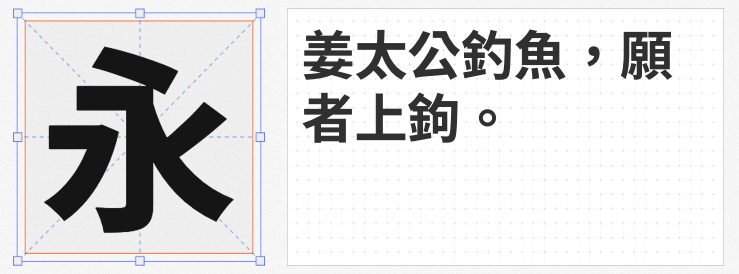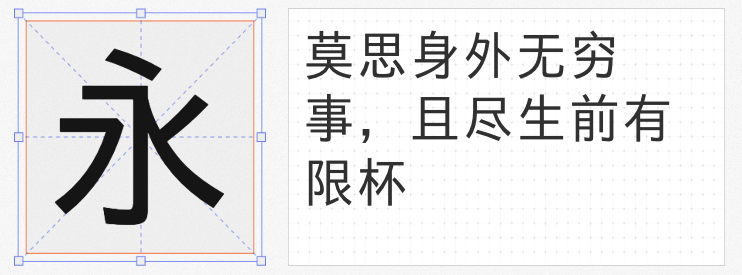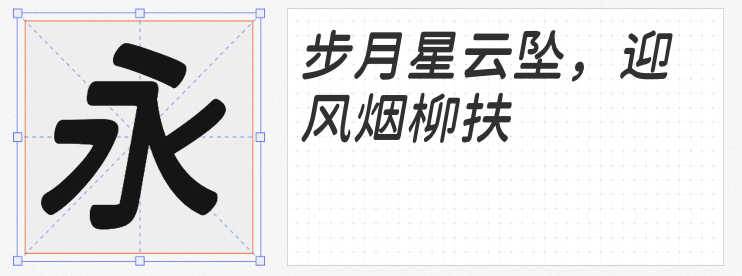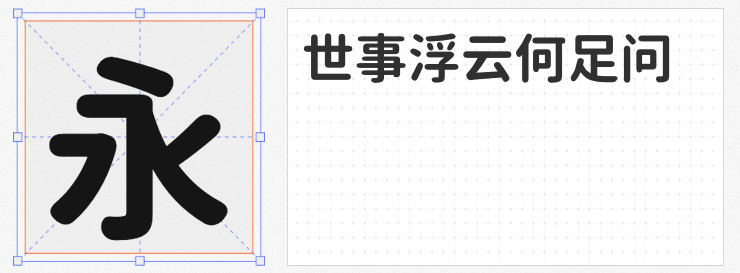
在商业设计领域,黑体因其简洁现代、辨识度高的特性,始终是视觉传达的核心工具。本文精选四款可免费商用的黑体字库,涵盖柔美风格、专业兼容性与时尚感,助力设计师在多元场景中精准表达创意。
基于江城圆体改造的江城月湖体,通过横向增粗、纵向减细的独特处理,形成“横粗竖细”的鲜明对比,搭配10度自然倾斜,赋予字体灵秀清美的气质。其圆润笔画中蕴含动感,既适合作为正文传递细腻信息,也可通过调整字号用于标题,强化视觉层次。例如,在女性品牌海报或文化类宣传中,该字体能通过柔美风格与内容形成情感共鸣,同时保持黑体的清晰可读性。
作为思源黑体的衍生优化版本,梦源黑体TW W23通过实例化中间字重、合并曲线轮廓,解决了原版行高过大的问题,同时完整保留多语言支持、异体字库及高精度曲线等核心功能。其字重选择细腻丰富,从纤细到粗壮满足不同场景需求,尤其适合需要严格排版规范的项目,如企业年报、学术报告或国际化设计。
基于日本「03スマートフォントUI」改造的霞鹜尚智黑,通过横向压缩94%实现紧凑结构,搭配全新设计的英文字符与假名,呈现出稳重而不失时尚的视觉效果。该字体采用中国大陆规范字形,兼顾传统印刷习惯与现代设计需求,适用于科技产品界面、品牌标识或需要体现专业感的商业广告。
以思源黑体为基底,寒蝉圆黑体通过算法实现原汁原味的圆角化转换,在保留黑体骨架的同时,以柔和曲线消解尖锐感,形成独特的现代风格。其超粗版本减少圆角曲率,确保视觉冲击力,适合年轻化品牌设计、社交媒体海报或需要突出亲和力的场景。